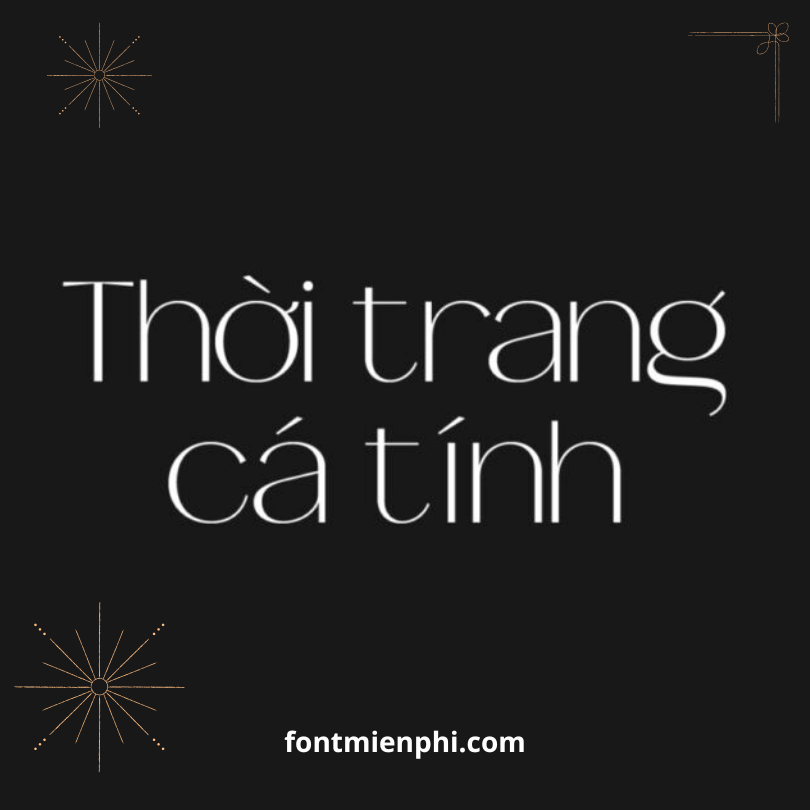
Font Việt hóa 1FTV VIP Signora Wide
Font Việt hóa 1FTV VIP Signora Wide – Kiểu Chữ Sang Trọng Đa Dụng Cho Thiết Kế Chuyên Nghiệp
1. Tổng Quan
Font 1FTV VIP Signora Wide là bộ font chữ cao cấp thuộc bộ sưu tập 1FTV VIP, được thiết kế với phong cách sang trọng, hiện đại và hỗ trợ đầy đủ tiếng Việt. Với kiểu chữ rộng (Wide) thanh lịch, font phù hợp cho các dự án đòi hỏi tính thẩm mỹ cao như thiết kế thương hiệu, poster, logo, và giao diện website.
2. Đặc Điểm Nổi Bật
✅ Hỗ Trợ Tiếng Việt Chuẩn
• Bao gồm đầy đủ dấu câu, ký tự Unicode, đảm bảo hiển thị sắc nét trên mọi nền tảng.
✅ Phong Cách Thiết Kế Độc Đáo
• Kiểu chữ Wide (rộng) tạo điểm nhấn mạnh mẽ, phù hợp cho:
• Tiêu đề banner
• Logo công ty
• Thiết kế bao bì
• Typography nghệ thuật
3. Ứng Dụng Đa Dạng
Thiết kế đồ họa: Poster, brochure, namecard, bao bì sản phẩm.
Digital Marketing: Banner quảng cáo, social media, landing page.
Nghệ thuật Typography: Chữ kỷ niệm, quà tặng, tranh treo tường.